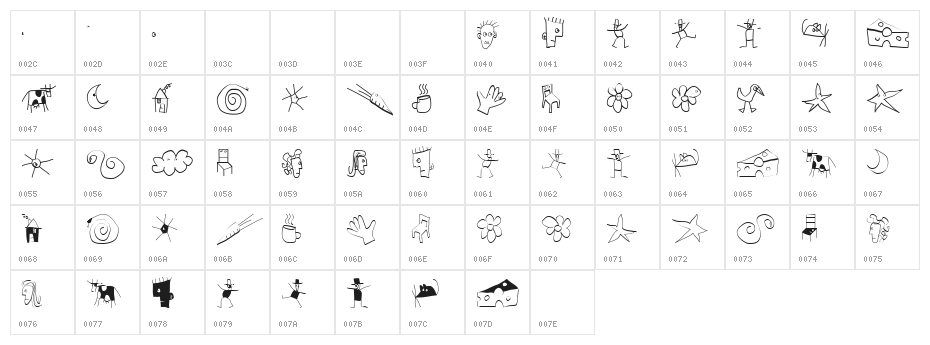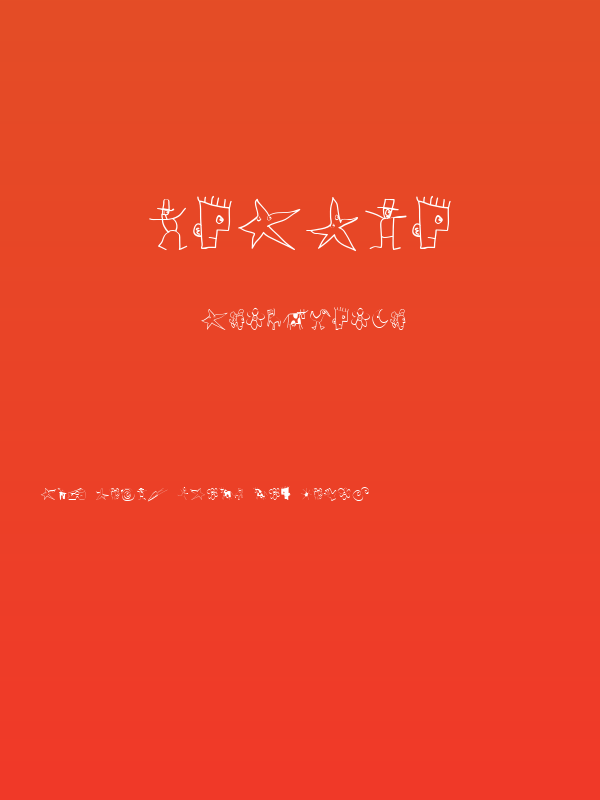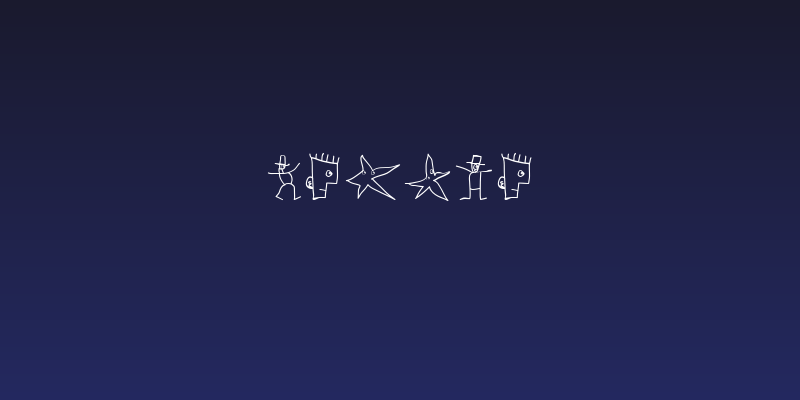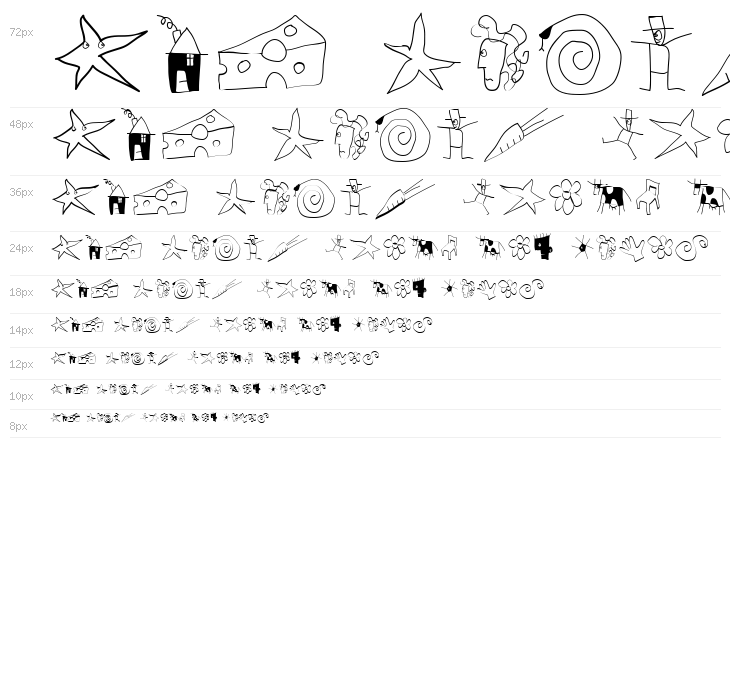
BatsDa Font
✎ Dingbats
| Gesamtstil | Whimsical |
| Anwendungsfall | Decorative elements, Artistic designs |
| Vorgeschlagene Projekte | Ideal for creative projects such as children's books, greeting cards, scrapbooking, and artistic posters. |